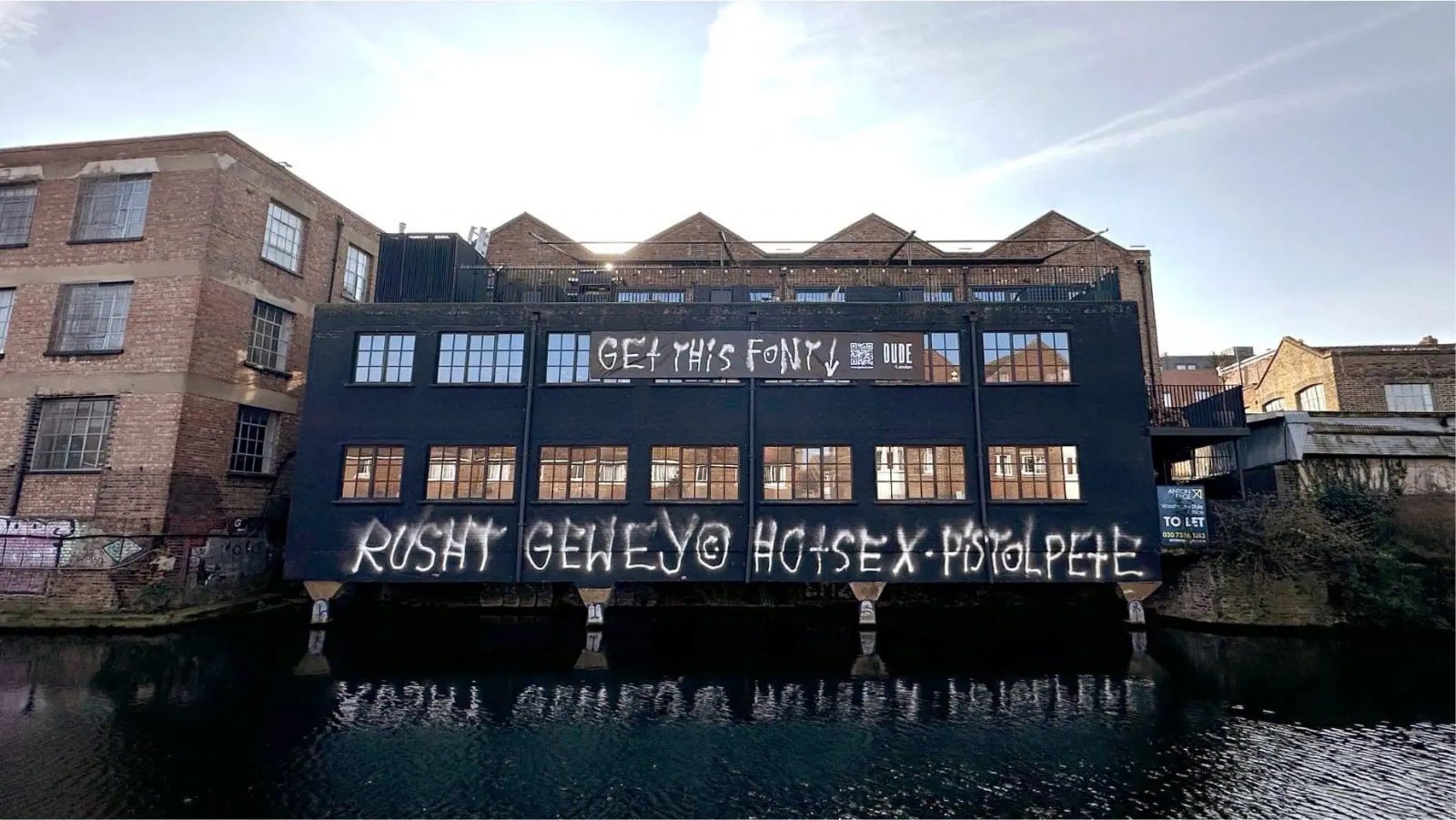
Mặt tiền văn phòng agency DUDE bị vẽ bậy, họ quyết định không xoá mà biến chính graffiti đó thành bộ font “Trả Thù” để đem bán.
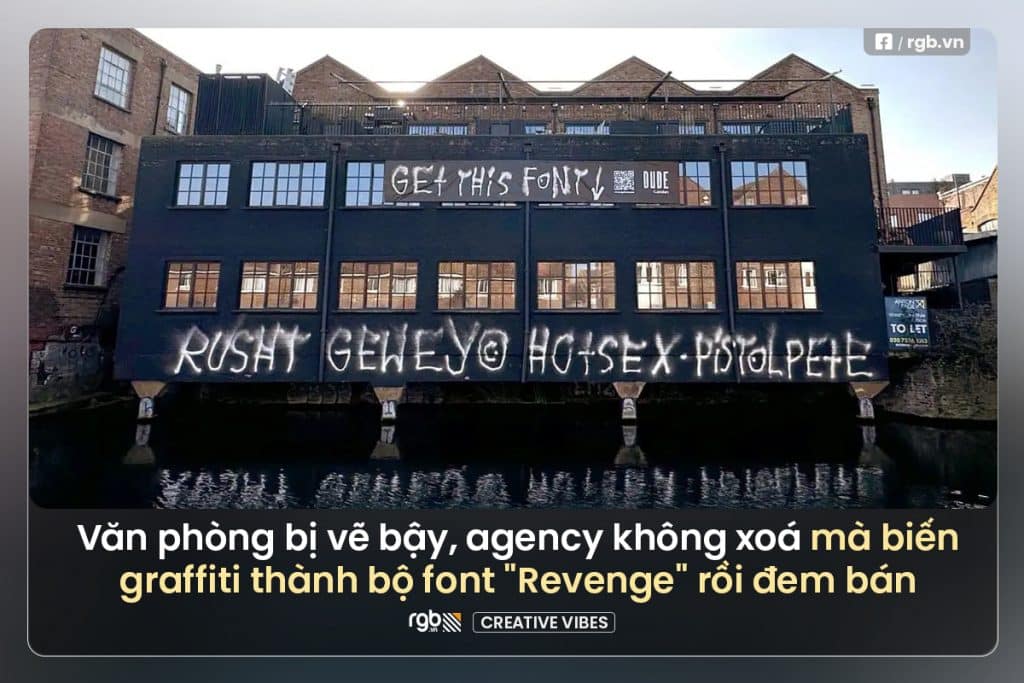
DUDE London, một agency sáng tạo phát hiện mặt tiền văn phòng của mình bị bôi bẩn bởi những dòng graffiti nguệch ngoạc. Thay vì đơn giản là sơn lại tường, họ chọn một cách “phản đòn” đầy sáng tạo và hài hước: biến những nét vẽ graffiti đó thành một bộ font chữ độc đáo mang tên “Revenge Font” (Bộ Font Trả Thù) và đem bán.
Những dòng chữ vẽ bậy trên tường của DUDE London không có nhiều ý nghĩa, chỉ là một mớ hỗn độn với các từ ngữ ngẫu nhiên như “Rusht Gewey Hotsex Pistol Pete”. Thay vì coi đây là một sự phiền toái, nhóm sáng tạo của DUDE đã quyết định chuyển đổi từng ký tự trong graffiti thành một bộ font chữ hoàn chỉnh.
Mỗi chữ cái trong bộ font đều dựa trên các đường nét gốc của graffiti, tạo nên một typography thô, mang đậm chất đường phố. Bộ font “Revenge Font” không chỉ là một phản ứng hài hước, mà còn trở thành biểu tượng của sự sáng tạo và khả năng thích nghi.
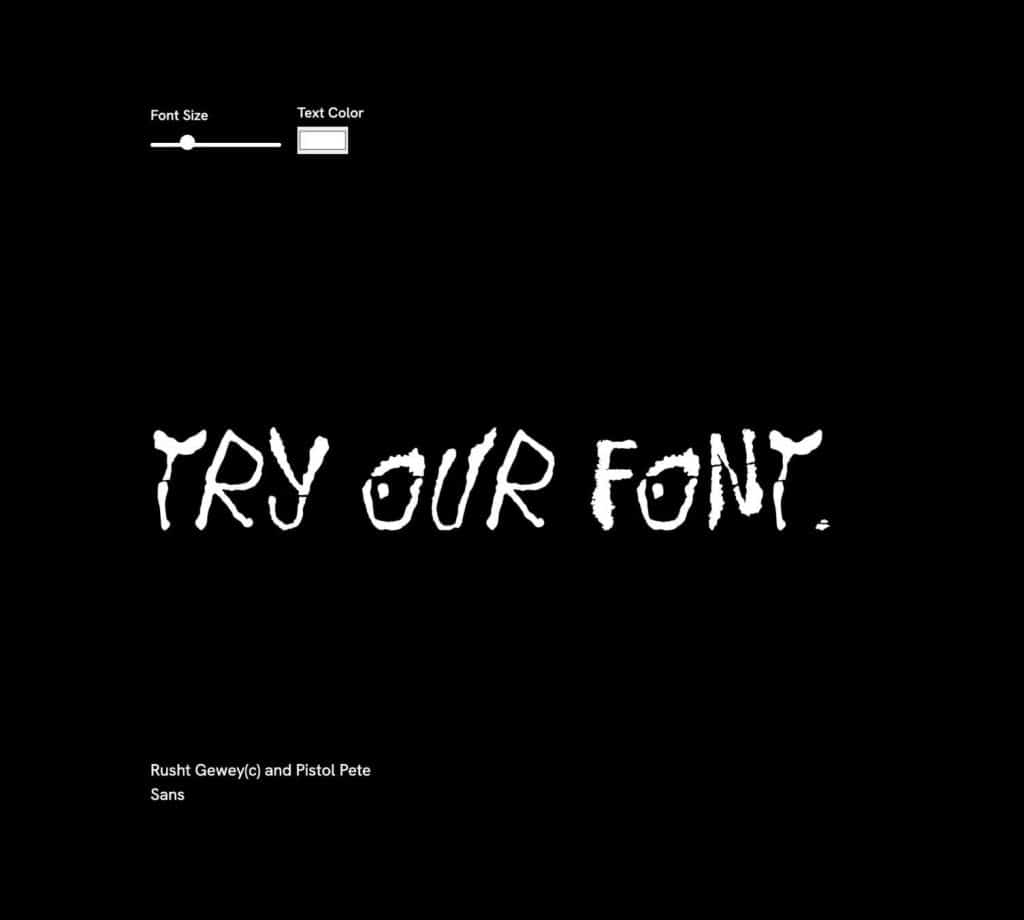
Không chỉ dừng lại ở việc tạo ra một bộ font chữ, DUDE London quyết định dùng “Revenge Font” để hỗ trợ cộng đồng nghệ thuật. Tất cả doanh thu từ việc bán bộ font sẽ được quyên góp cho tổ chức Bow Arts, nơi hỗ trợ các nghệ sĩ trẻ và giáo dục nghệ thuật tại London – một cách biến hành vi phá hoại thành một nguồn tài trợ thực sự cho nghệ thuật.
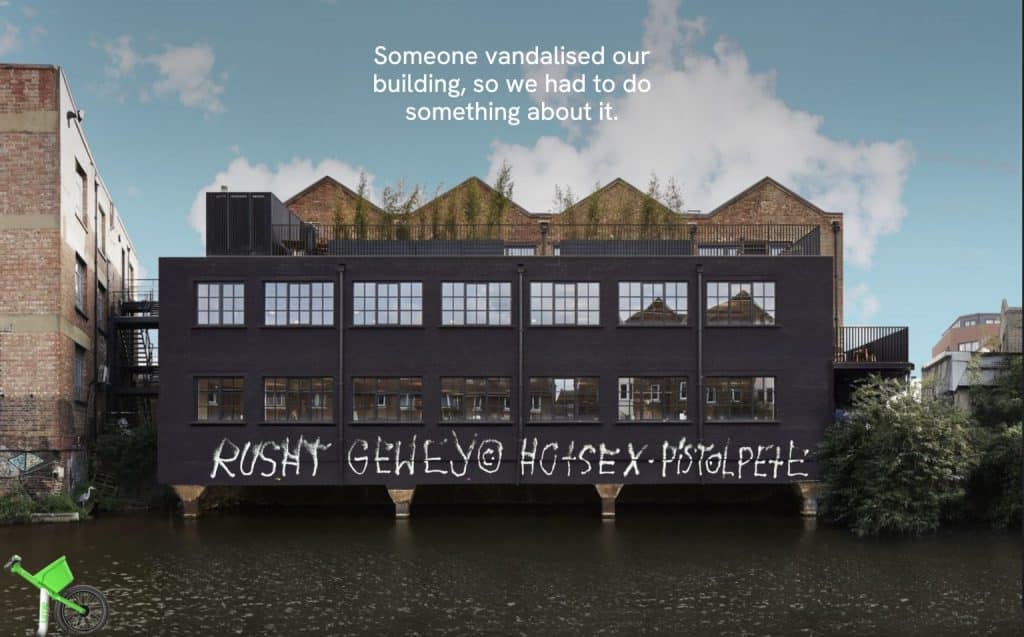
Để quảng bá bộ font, DUDE London đã treo một banner ngay trước văn phòng với một mũi tên chỉ về phía graffiti ban đầu cùng mã QR dẫn đến trang tải xuống Revenge Font. Để lan toả chiến dịch, DUDE London còn tạo ra một website riêng (revengefont .com) để người dùng có thể trải nghiệm bộ font trước khi mua hoặc đóng góp trực tiếp cho quỹ Bow Arts. Ngoài ra, người xem còn có thể tham gia sự kiện ra mắt “Revenge Font” – một buổi tiệc mang đậm tính cộng đồng.
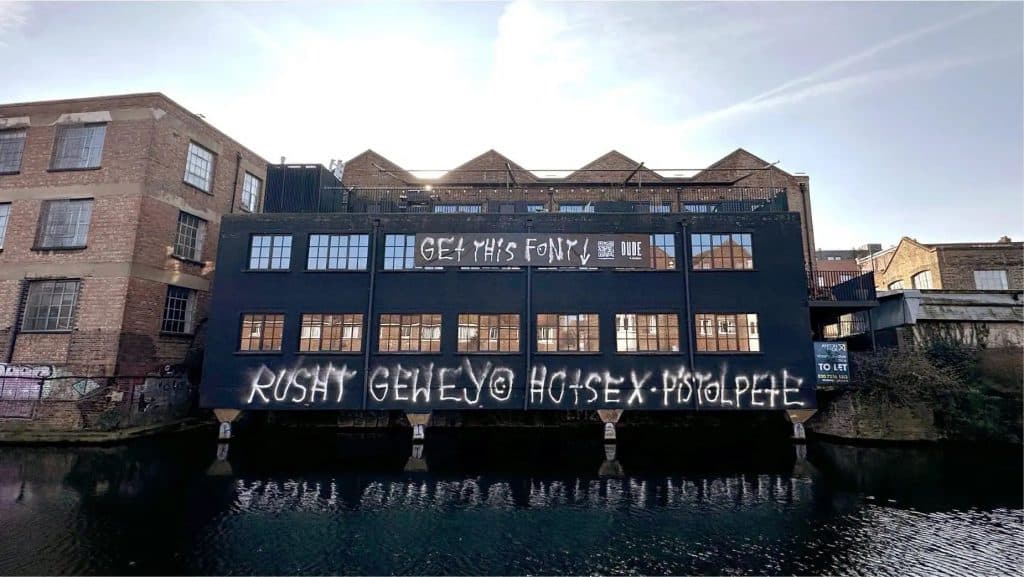
Theo Joe Ribton, một trong những giám đốc sáng tạo của DUDE London:
“Khi những ‘vị thần graffiti’ tặng chúng tôi một thứ bừa bộn và khá vô nghĩa, chúng tôi quyết định dùng sự sáng tạo để đáp trả.”
Đây là một minh chứng rõ ràng rằng khi đối mặt với rủi ro, đôi khi cách phản kháng tốt nhất chính là sáng tạo và biến nó thành một giá trị thực sự.